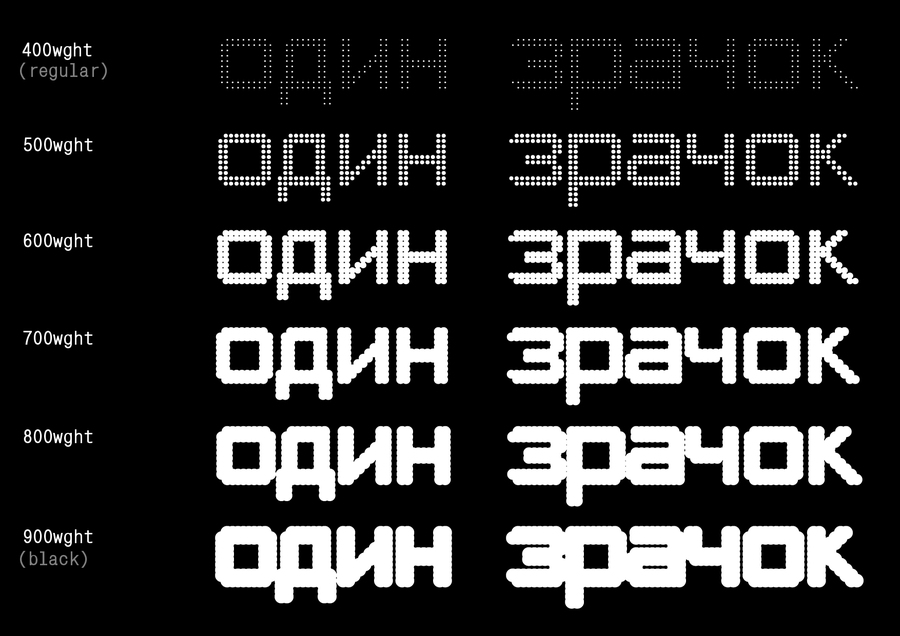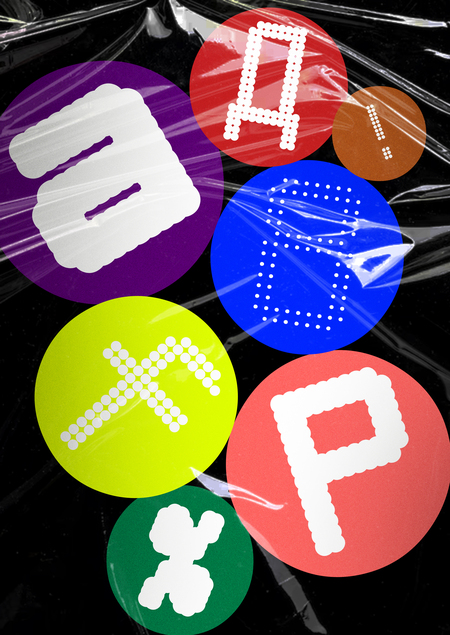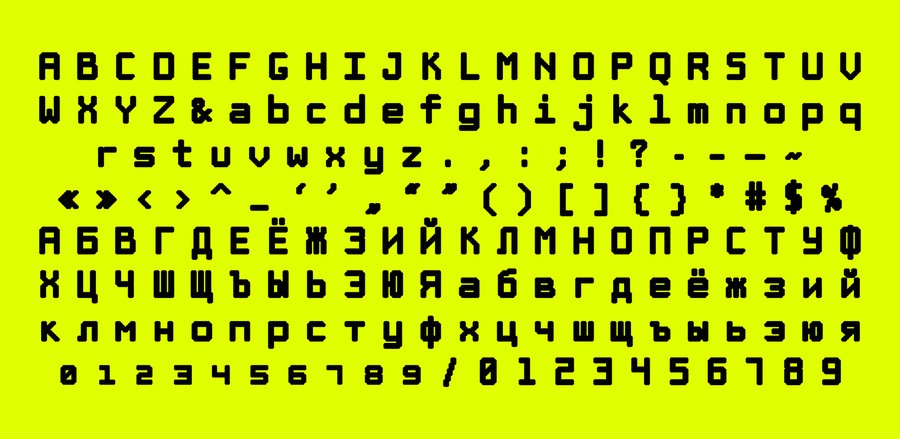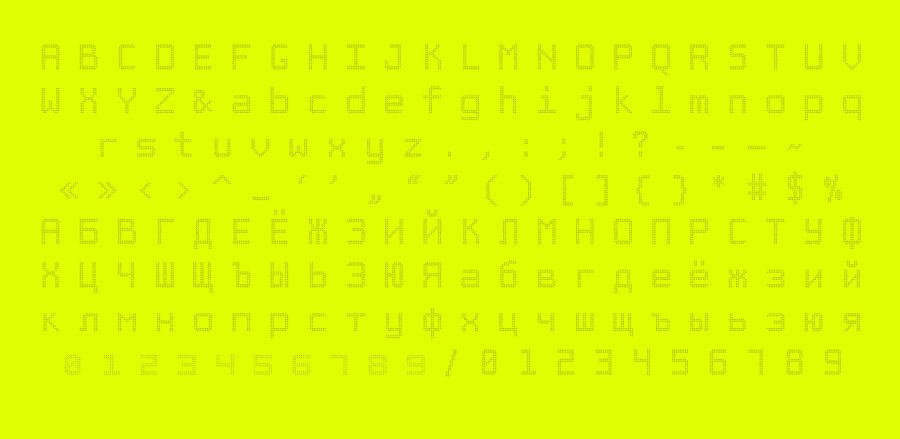
шрифт «pupil» — моноширинный вариативный модульный шрифт, вдохновленный зрачками человека. модулем шрифта является круг (зрачок), расширяющийся от regular до bold.
касса шрифта в начертаниях regular и black
разные насыщенности шрифта